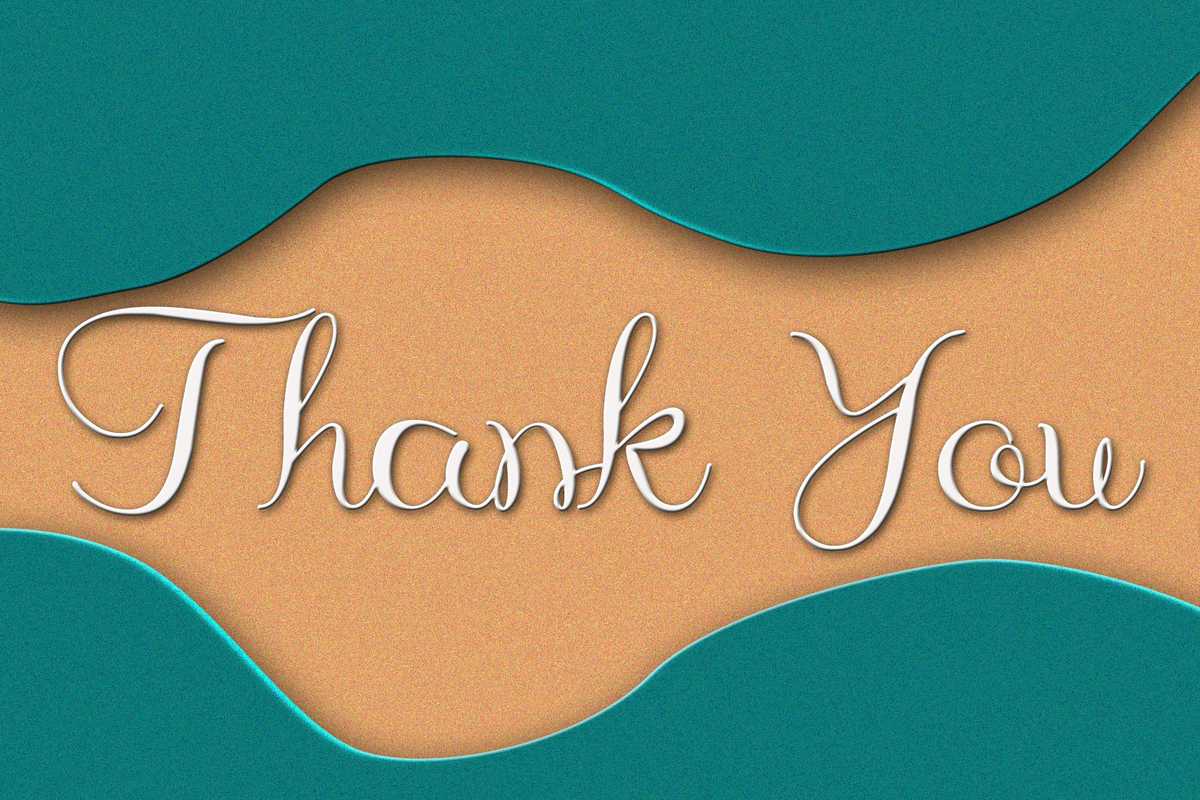
Baladewa是HizartDesignStudio的ScriptFontBy HizartDesignStudio。它有美丽的彩色字母,可以让您的设计清晰可见。BaladewaFonts是徽标、问候卡、包装设计、耐磨性、工艺设计、任何项目、书名、婚礼宣传、包装、,还有更多。Baladewafont是HizartDesignStudio的ScriptFont。它有美丽的彩色字母,可以让您的设计在周末和周末都能看到。Baladewafont是徽标、问候卡、包装设计、耐磨性、工艺设计、任何项目、书名、婚礼宣传、包装等的完美之选。